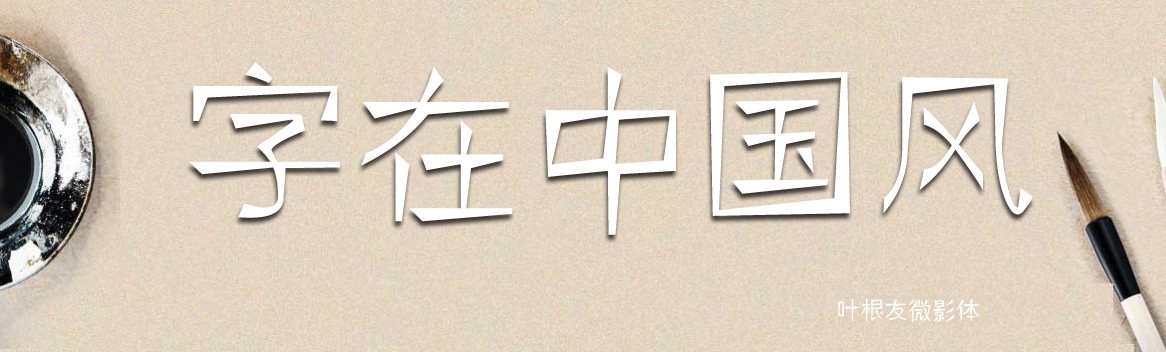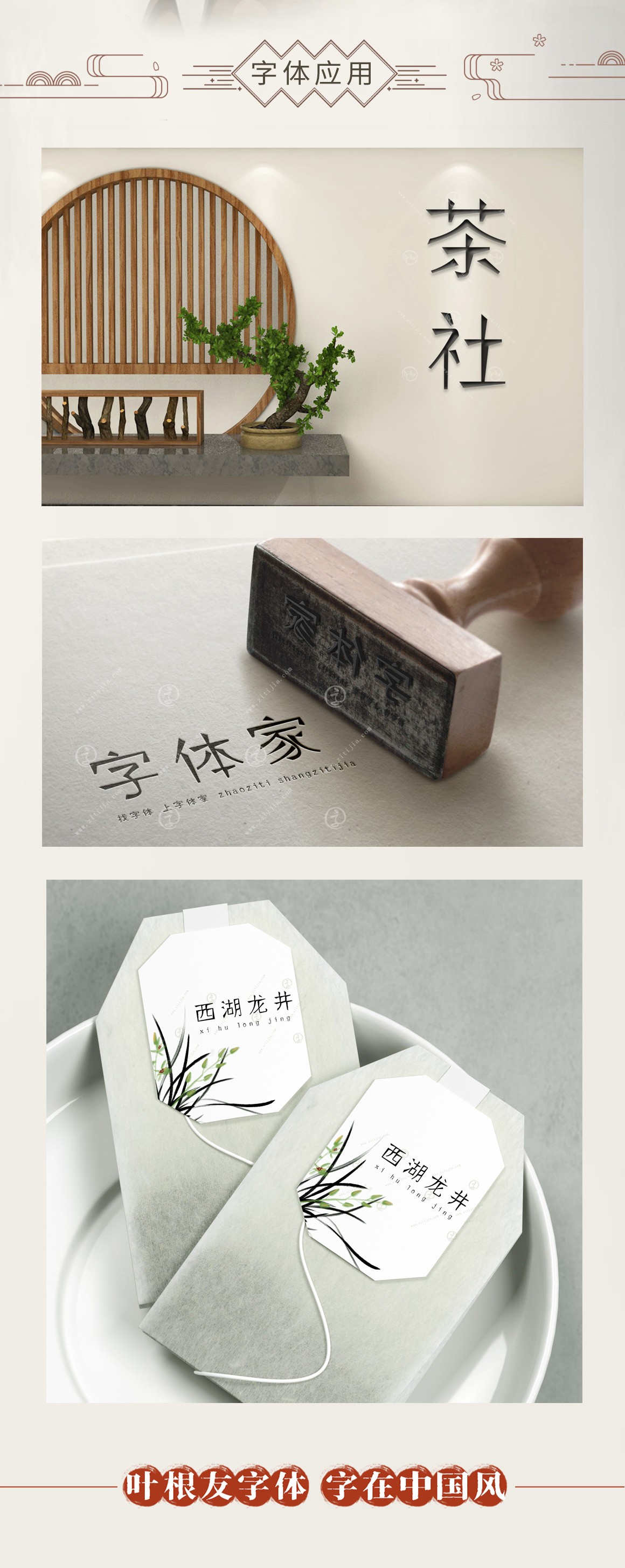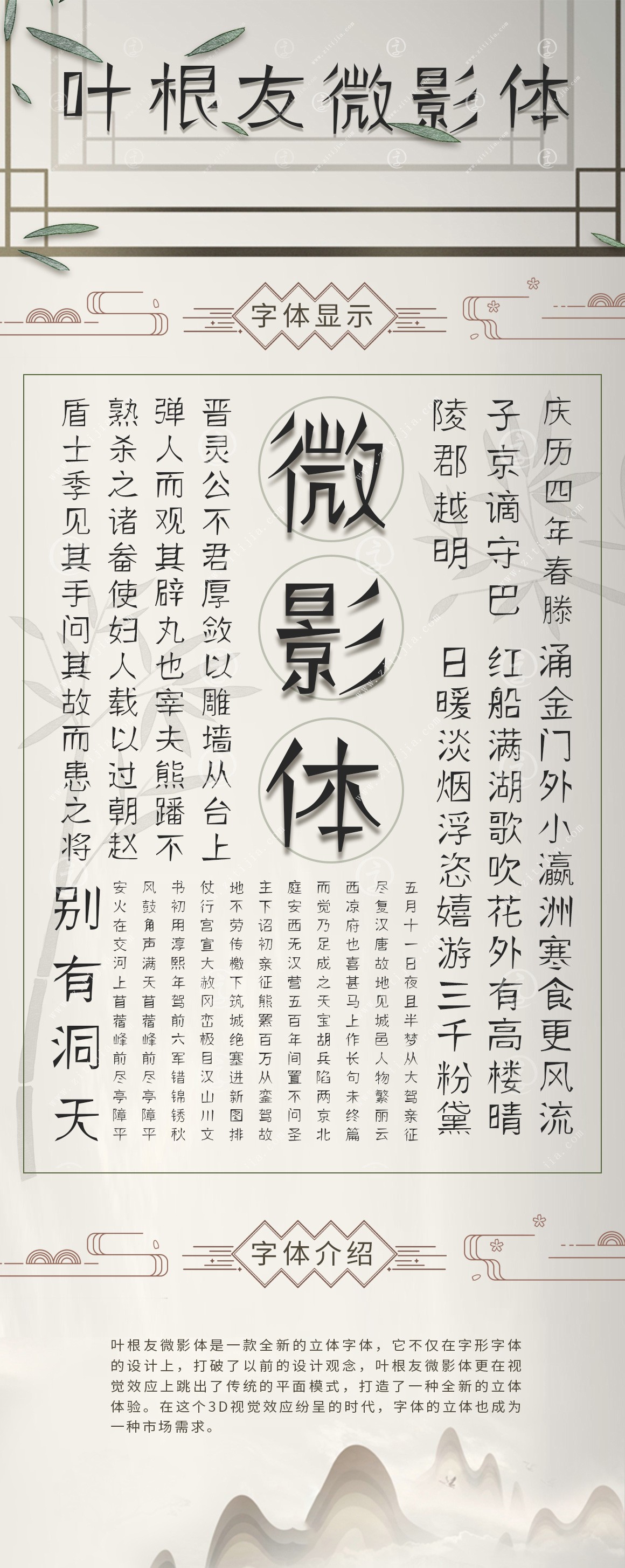
葉根友微影
字體作者:葉根友
創(chuàng)作年代:2013年
字體字?jǐn)?shù):6763個(gè)中文漢字以及其他英文字母和阿拉伯?dāng)?shù)字
字體介紹
葉根友微影體是一款全新的立體字體,它不僅在字形字體的設(shè)計(jì)上,打破了以前的設(shè)計(jì)觀念,葉根友微影體更在視覺(jué)效應(yīng)上跳出了傳統(tǒng)的平面模式,打造了一種全新的立體體驗(yàn)。在這個(gè)3D視覺(jué)效應(yīng)紛呈的時(shí)代,字體的立體也成為一種市場(chǎng)需求。